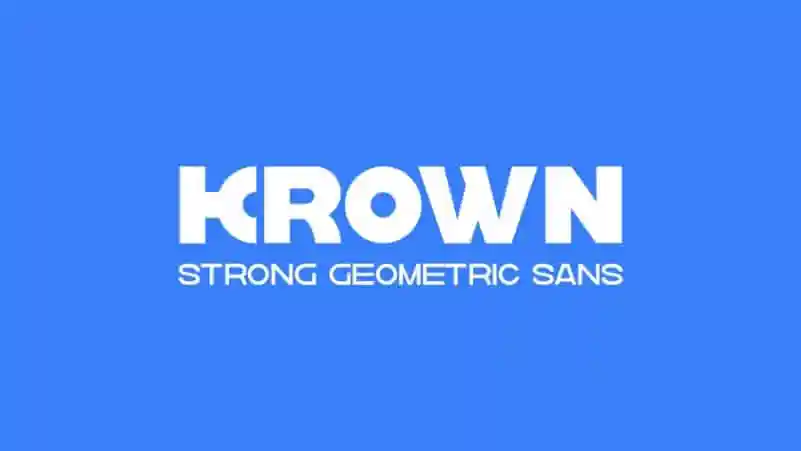
Krown Sans Serif Font Family – Download Grátis
A Krown Sans Serif é uma nova família geométrica de fontes serifadas simples que se adapta facilmente a qualquer lugar do seu site, seja no topo da página ou como texto pequeno com conceito variável. Através desta fonte, você terá um aspecto arredondado e energético, certamente perfeito para os millennials – uma categoria que é particularmente adequada à utilização por agências digitais e criativas. Ideal para websites jovens e inovadores, esta família de fontes permite o uso aprimorado da estética geométrica, mantendo-se atual e dinâmica. Engajue seus visitantes com esse novo design.